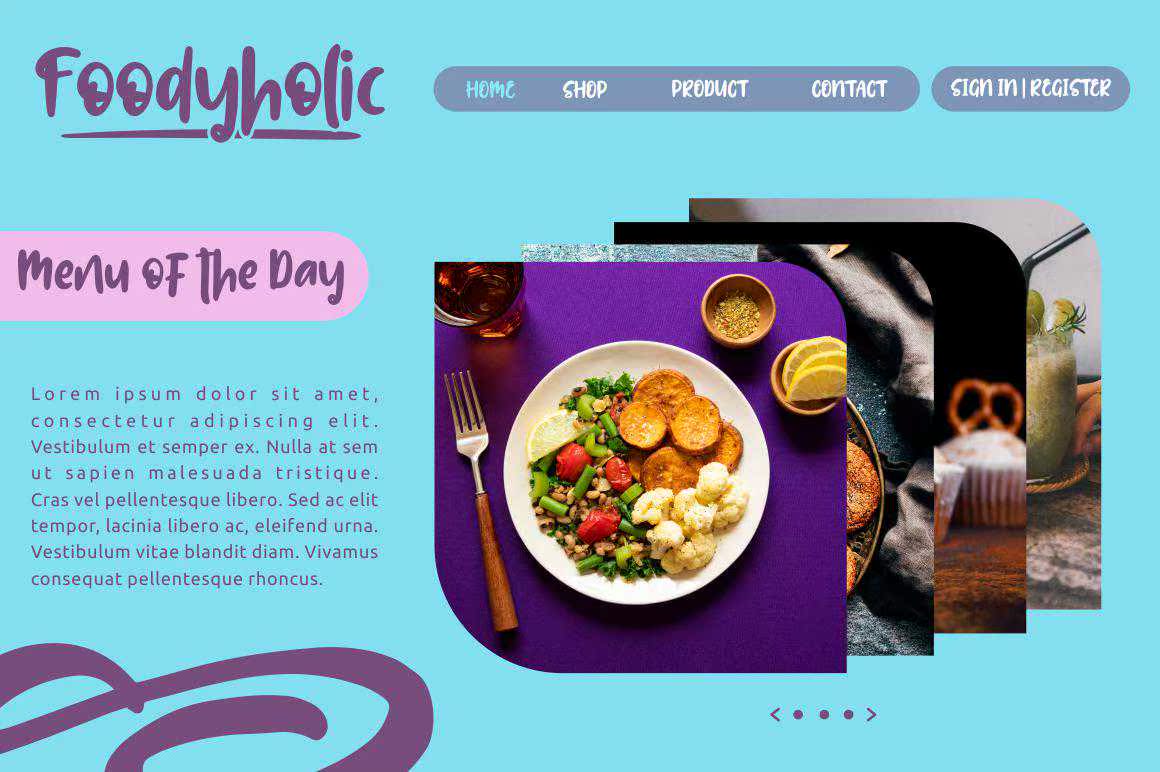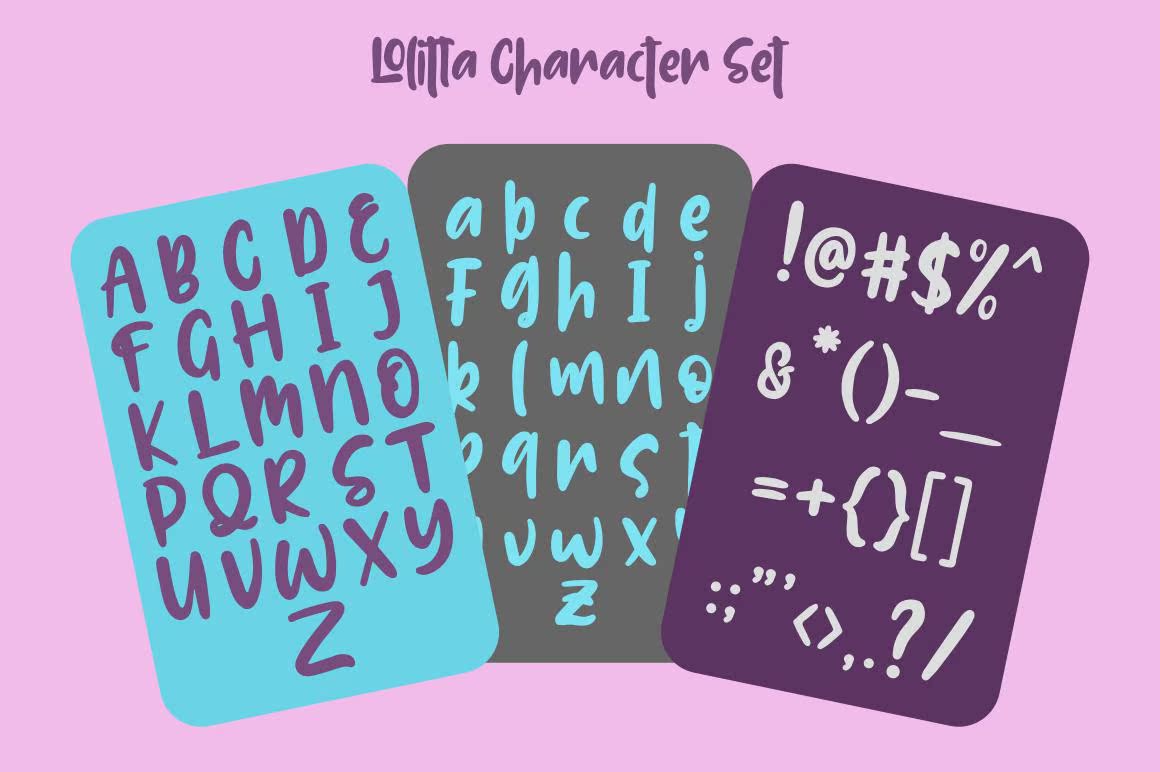
LOLITTA是BoldandFund显示字体。它带来了快乐和快乐。灵感来自BoldandFunmarker的BoldandStrong风格。该字体适用于显示、文本、打印、品牌、标牌、,在YLAYOUT的设计中,具有最佳字符的字体是粗体和基本显示字体。它带来了欢乐和快乐。灵感来自于具有粗体和强烈风格的ABOLD和FUN MARKER。该字体用于显示、文本、打印、品牌、标牌,具有最佳字符的YLAYOUT设计